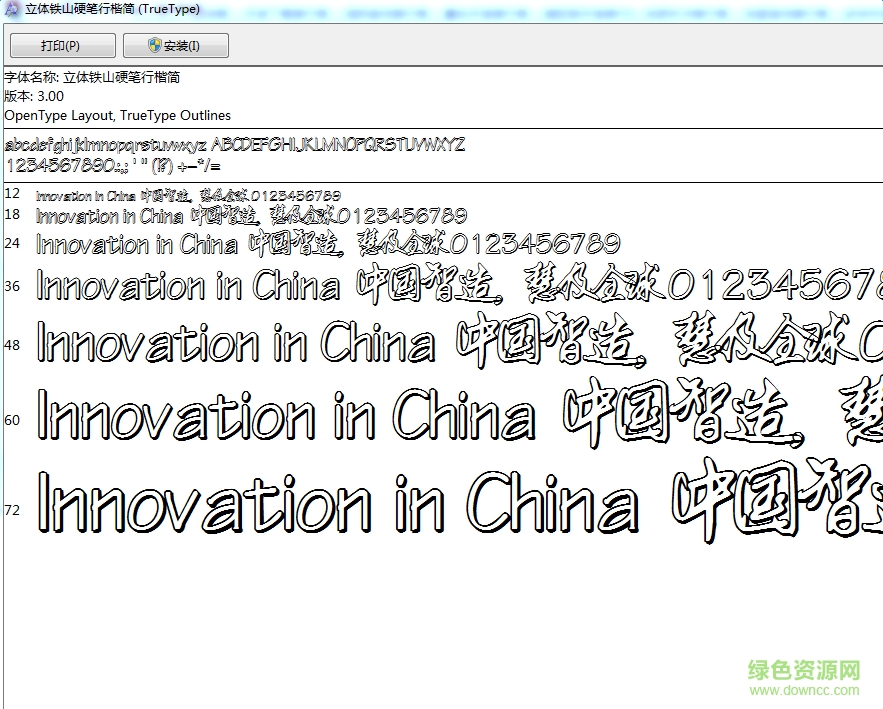
立體鐵山硬筆行楷字體是一款時(shí)尚酷炫風(fēng)格字體軟件,硬筆行楷體筆畫繼承經(jīng)典楷體獨(dú)有特色,以立體效果展示給用戶,非常有創(chuàng)意,整體效果非常震撼酷炫,還有更多好看字體歡迎來(lái)綠色資源網(wǎng)下載體驗(yàn)!
立體鐵山硬筆行楷字體是一款應(yīng)用于藝術(shù)設(shè)計(jì)方面的簡(jiǎn)體中文字體,該字體呈立體形狀,尾部的甩尾有力且有豐富的筆觸細(xì)節(jié),大字效果突出且引人注目;并且最大程度還原作者書寫字形,細(xì)節(jié)表現(xiàn)完整,且字庫(kù)完整,可以廣泛應(yīng)用于名片設(shè)計(jì)、新聞媒體、宣傳海報(bào)、ppt、影視制作以及內(nèi)容用字等領(lǐng)域。